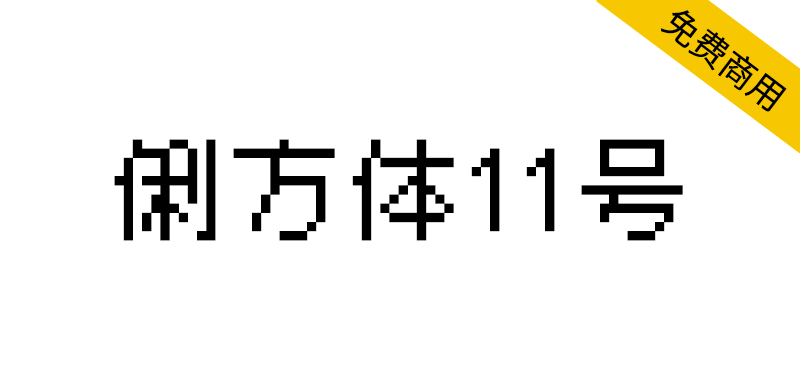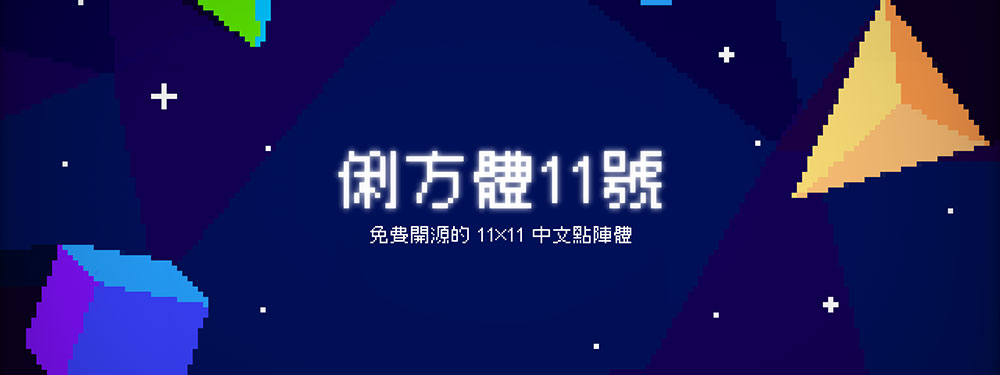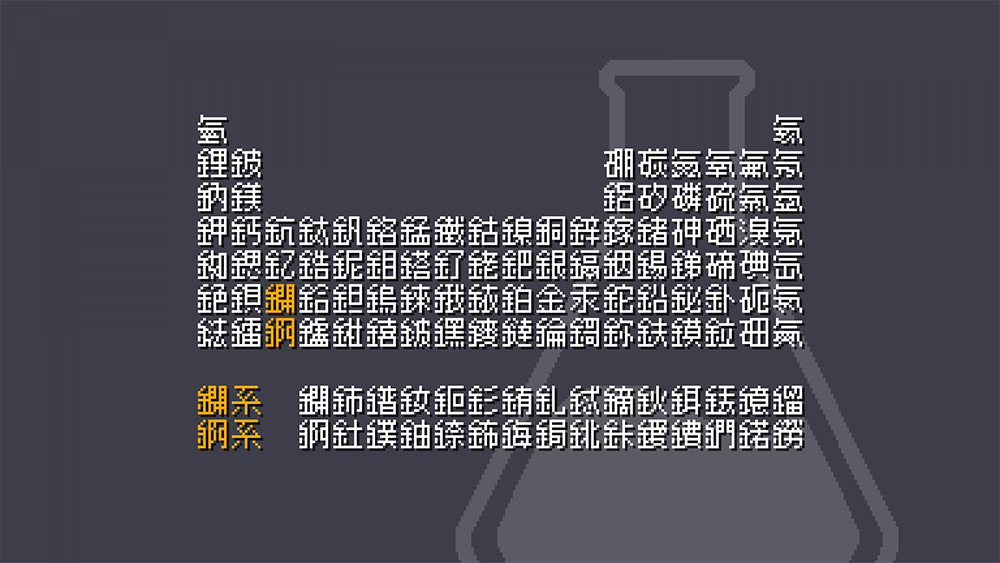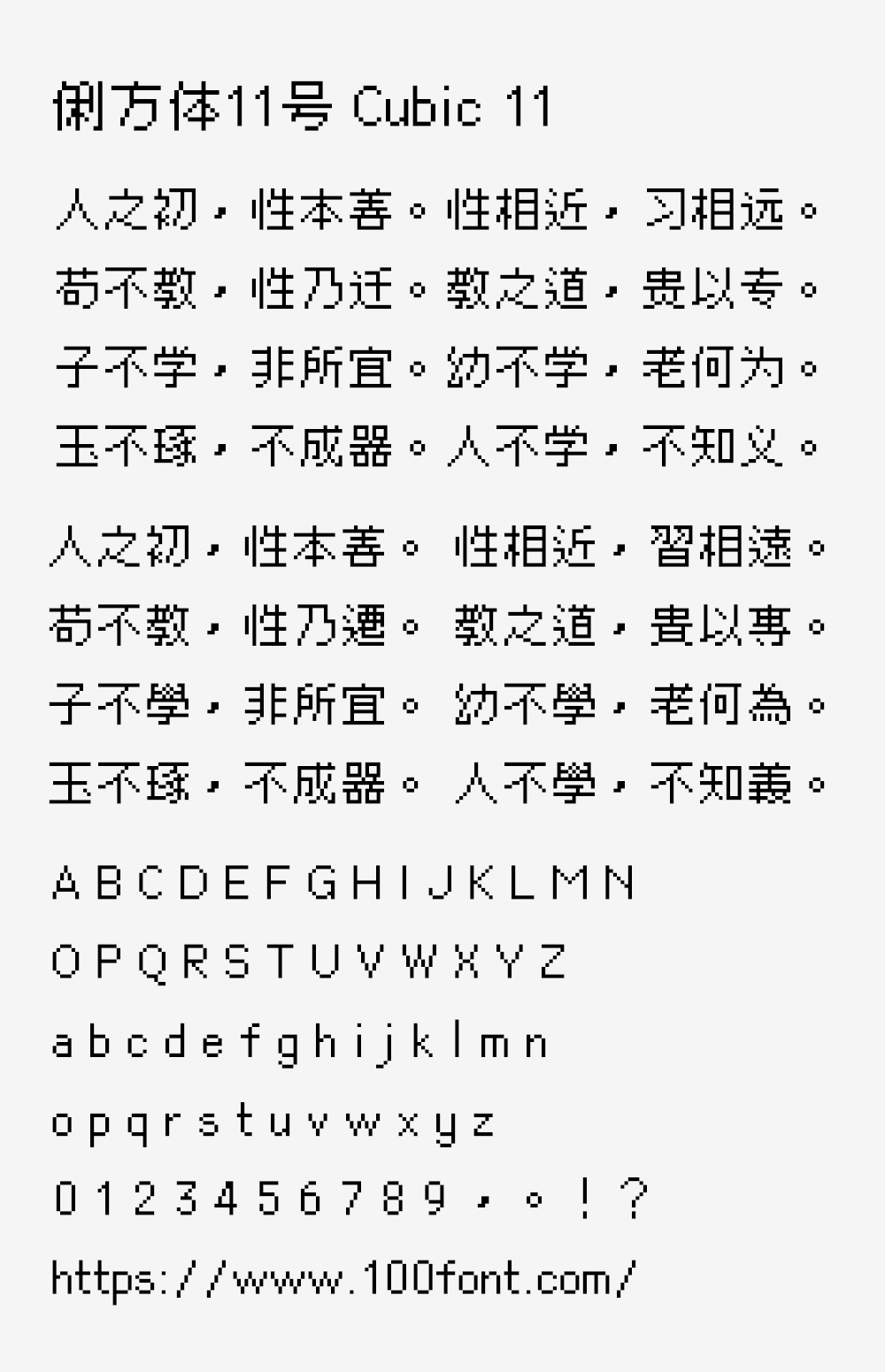
俐方体11号(Cubic 11)是基于M⁺gothic 12r 衍生的开源繁体中文点阵字体,可用于像素风格的游戏以及美术当中。本字体以日文字体M⁺gothic 12r 为基础替繁体中文进行修改与扩充,其中包括适用繁体中文的标点符号以及较符合台湾习惯的字形等。(注:该字体虽然也支持简体中文,但更适合用于繁体中文)
收录字数:常用国字标准字体4808字,Big5 第一字面5401字,IICore 台湾常用字T1A、T2A 及部分T2B,台客闽粤字,注音符号,GB 2312 Level-1,通用规范汉字表一级,元素周期表之所有元素字符。